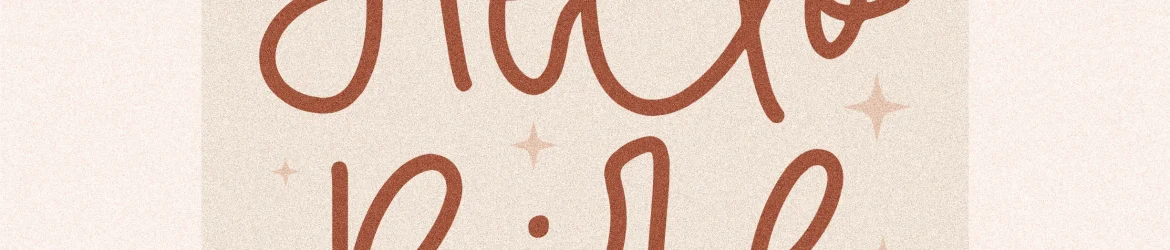
Hello Bird Font – Download Grátis
A fonte “Hello Bird Font” é uma elegante escolha para qualquer projeto que deseje dar um toque personalizado e autêntico. Com sua forma artesanal, esta fonte manuscrita foi projetada para oferecer versatilidade em diversos campos de aplicação. É perfeitamente adequada para criar logotipos, design de marcas, embalagens de produtos, mugs personalizados, cartazes e outras mídias publicitárias. Além disso, ela também é ideal para criações como etiquetas, selos de fotografia, materiais de eventos especiais, e até mesmo o selo do seu livro de capa ou sua identidade pessoal. Com a fonte “Hello Bird Font”, você pode garantir que seus projetos não apenas se destaquem na página ou no catálogo, mas também proporcionam um toque de autenticidade que irá realmente chamar atenção dos espectadores. Como designer ou aficionado pelo design, essa fonte é definitivamente uma escolha confiável para adicionar personalidade a qualquer projeto que você esteja criando.